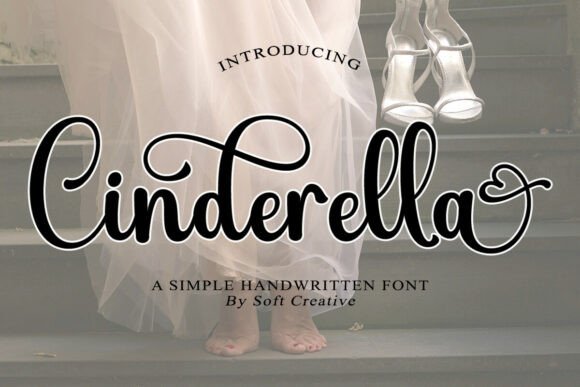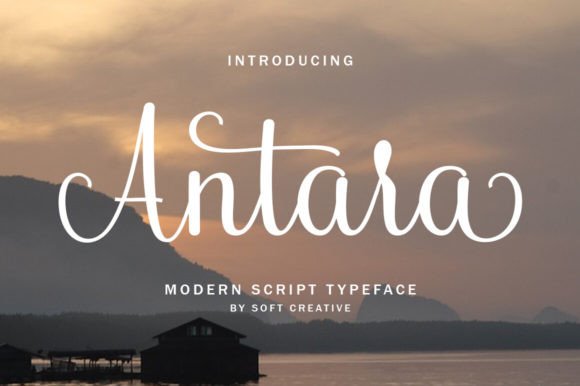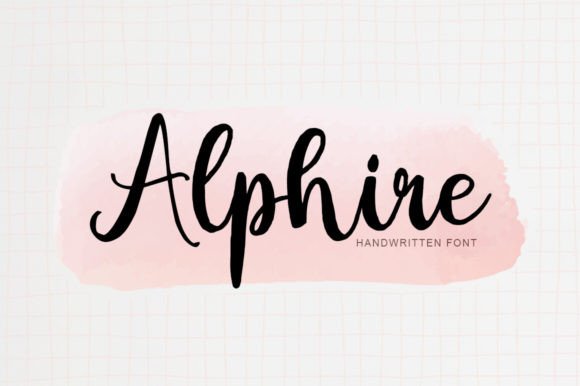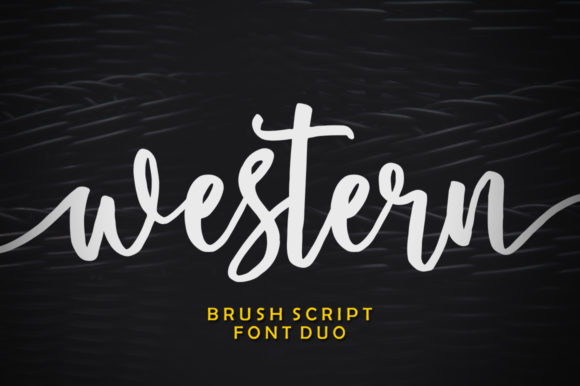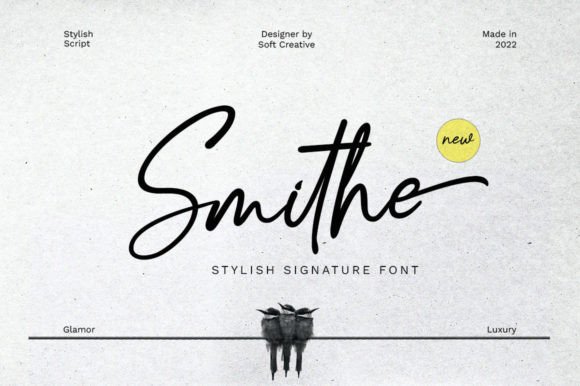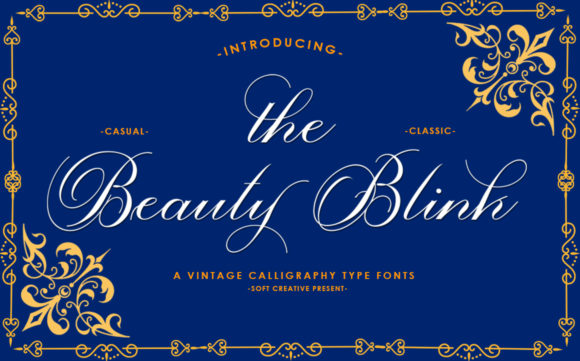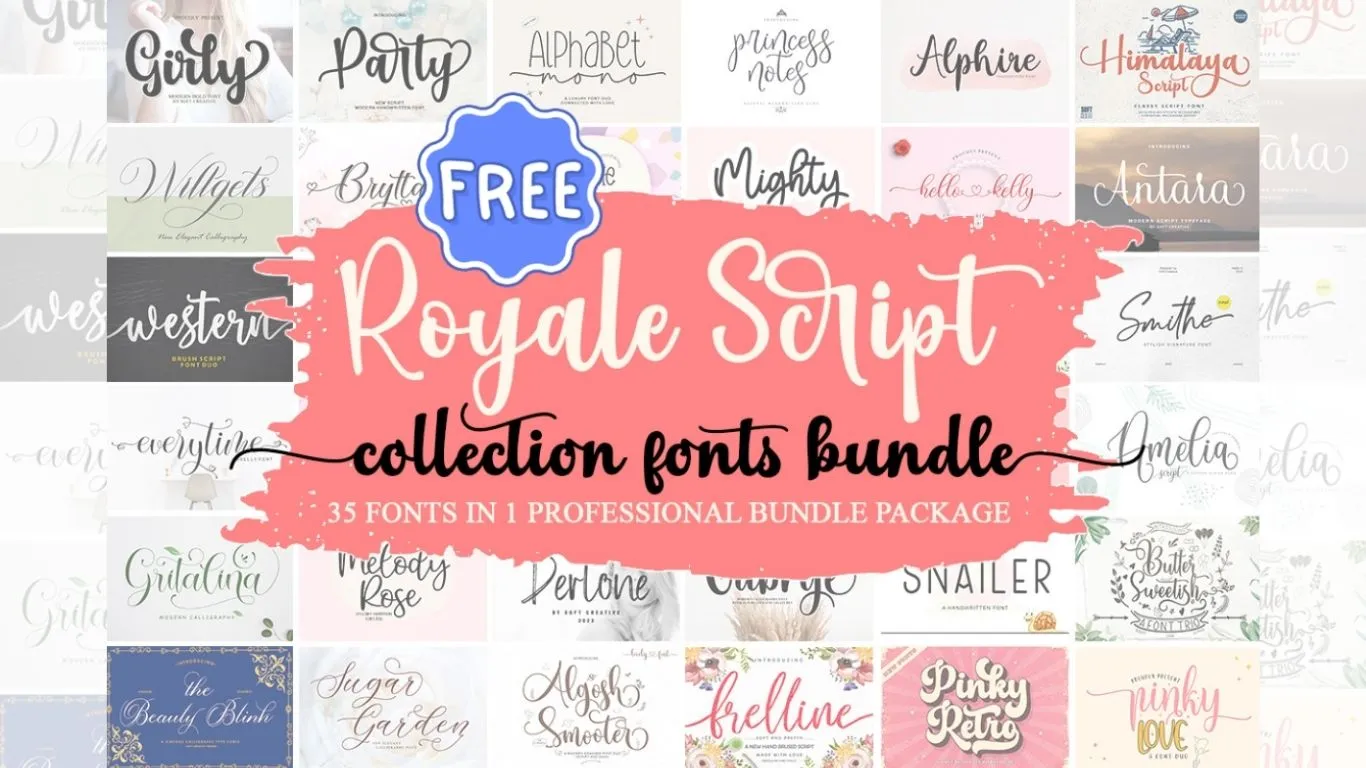
Creative Fabrica 免費字體包 Royale Script Collection Font Bundle
字體包裡有什麼?
優雅浪漫系:Cinderella、Amelia Script、Melody Rose Duo、Silfer Queen、Bryttani、Hegia Sophia
甜美少女系:Girly、Pinky Retro、Pinky Love Font Duo、Barbie Sweet、Sugar Garden、Butter Sweetish、Princess Notes
現代手寫系:Alphire、Gabrye、Everytime、Frelline、Gritalina、Algosh Smooter、Willgets、Derlone
個性特色系:Western Duo、Himalaya Script、Snailer、Mighty、Rossie Dreams、Party
簽名書法系:Smithe Signature、Hello Kelly、Hello Flansher、Dagestan Script、Antara
雙字體組合 (Duo):Alphabet Mono Duo、Western Duo、Pinky Love Font Duo、Melody Rose Duo
其他:The Beauty Blink、Glow Better